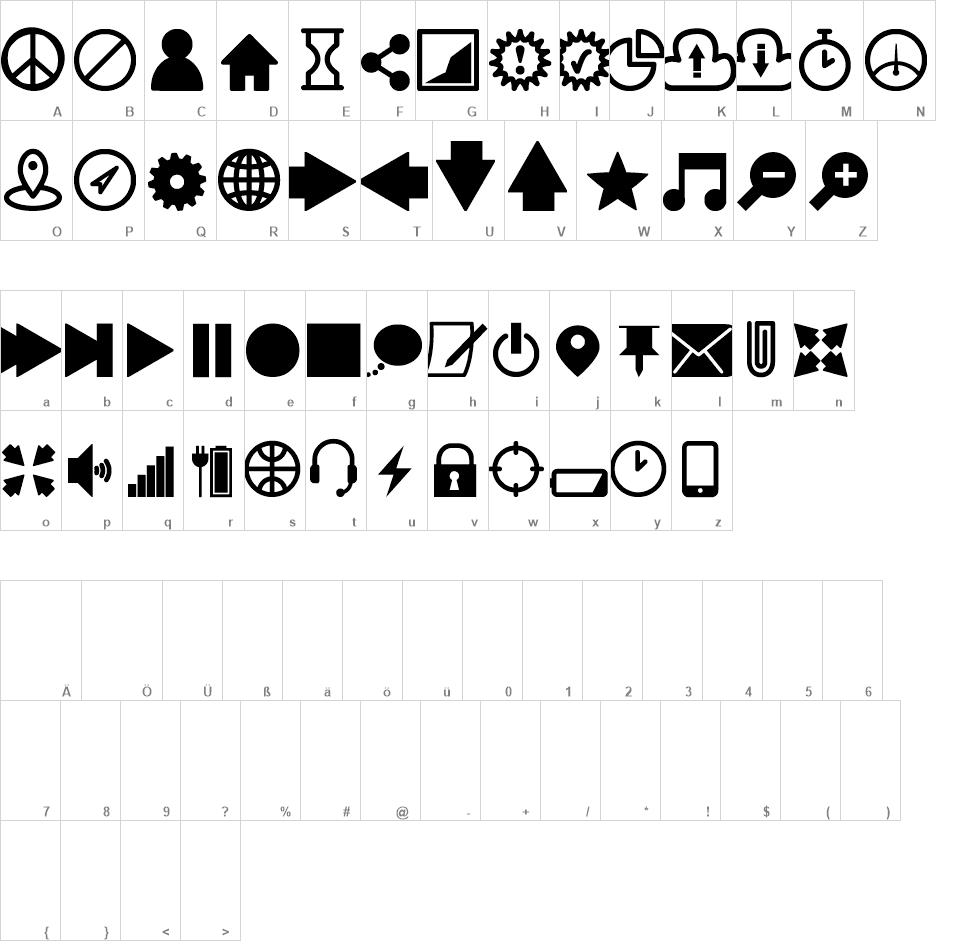
Icons South St - Web Sembol
Icons South St - Web Sembol font
Kartensymbole, Home-Symbol, Start Stop-Taste, Info-Blase, Notizblock, Brief-Mail-Symbol, Handy-Symbol, Gebührensymbol, Musik-Symbol, Zoom-in-Symbol, öffnen Schließen-Taste, Spoofing und Vergrößerung Einfach zu verwendende, unbegrenzte Farboption.